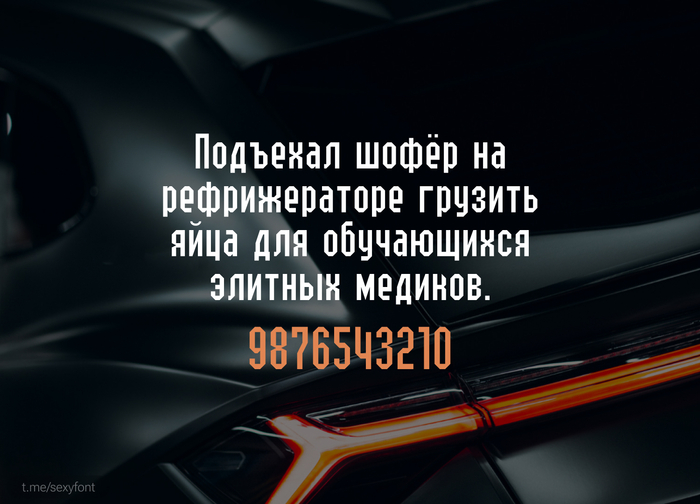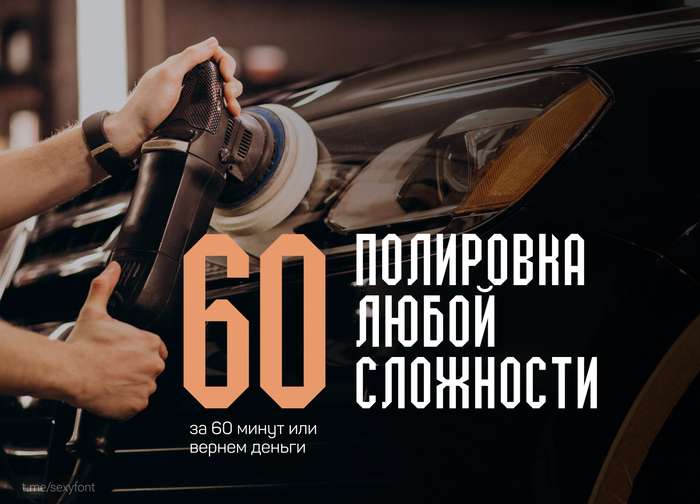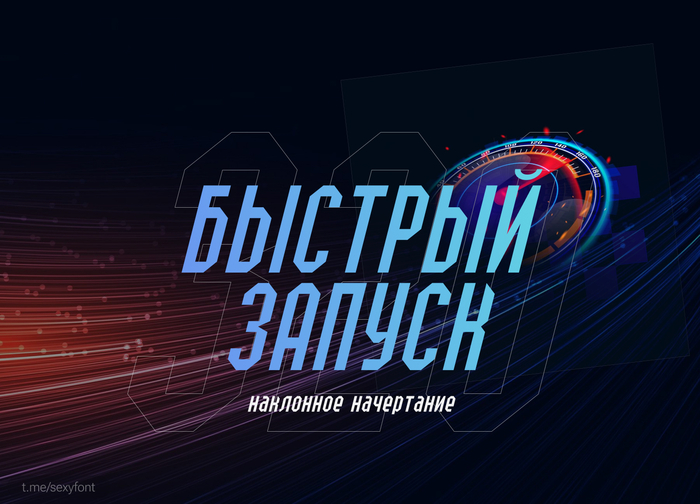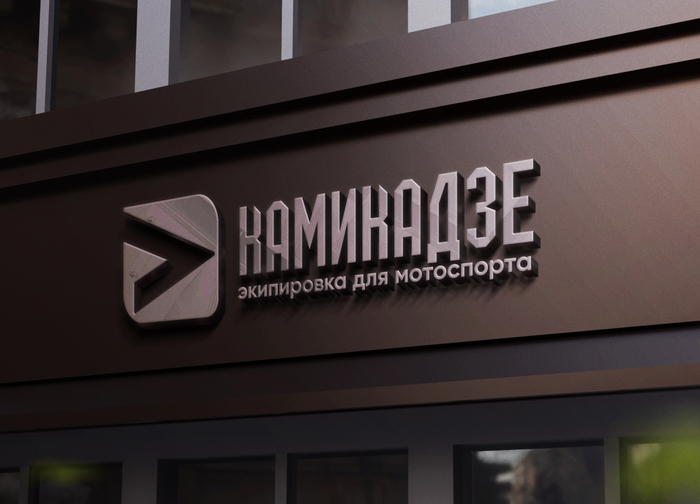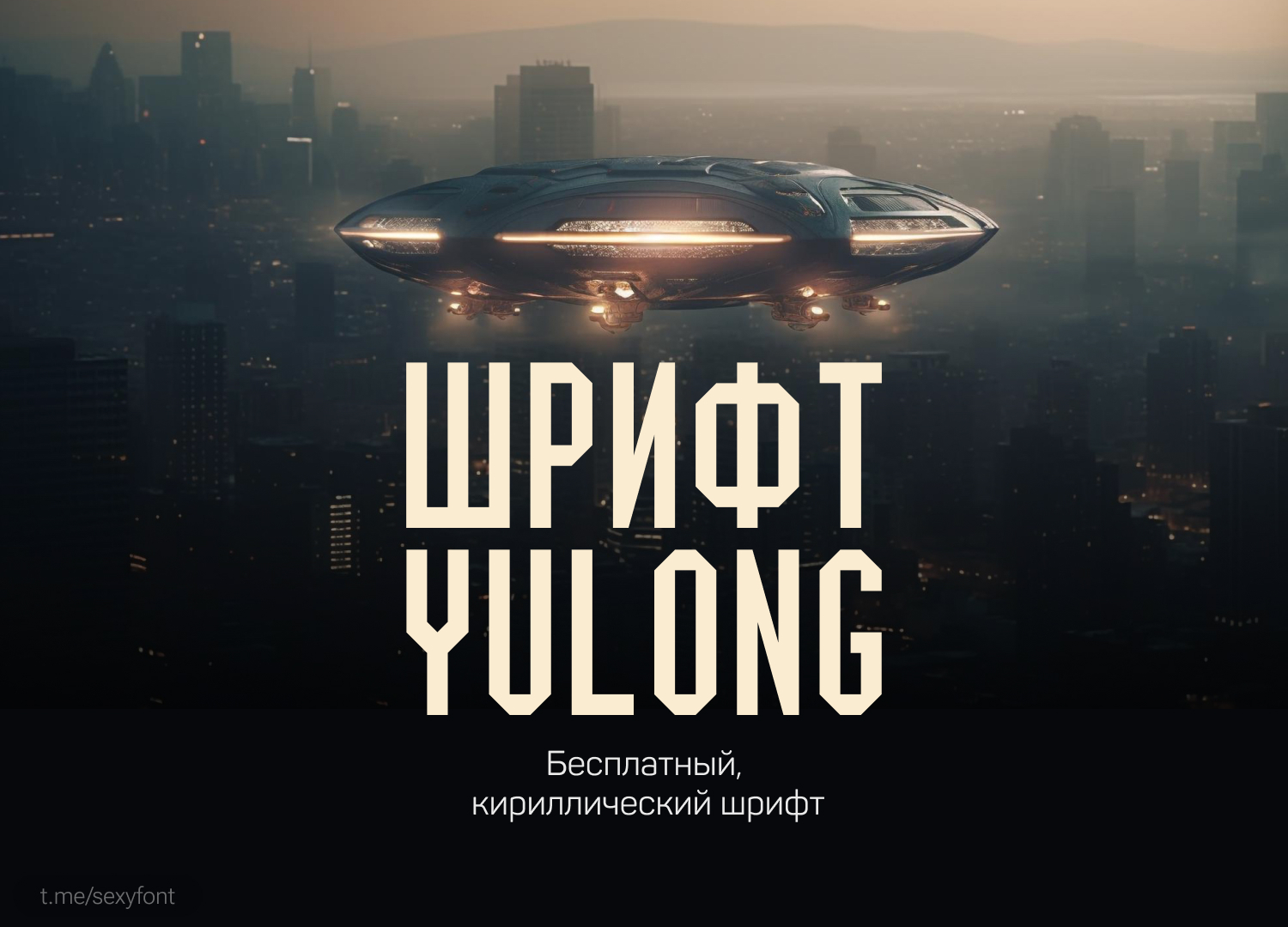
Шрифт Yulong. Бесплатная кириллица
Yulong. Сжатый геометрический шрифт, состоящий из двух стилей. Благодаря своему индустриальному виду шрифт подходит для логотипов, крупных заголовков, плакатов, вывесок, принтов, шрифтовых композиций, а также для макетов, связанных с технологиями и киберспортом.